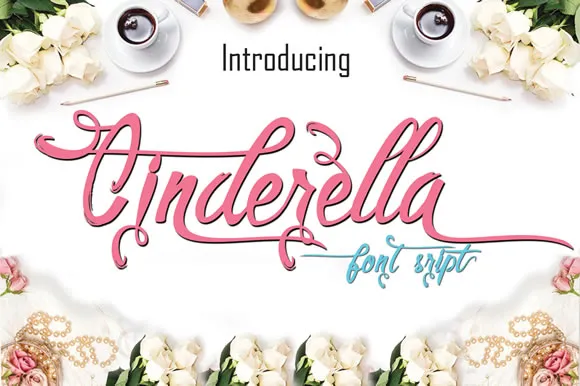
Cinderella Script Font – Download Grátis
Cinderella Script é uma fonte script moderna que transmite a elegância do antigamente refinado com a suavidade dos traços delicados. Embora seja uma criação moderna, apresenta detalhes meticulosos e linhas arredondadas criadas pelo traçado de um canivete pontiagudo e elegante. É uma mistura entre o clássico e o contemporâneo, trazendo uma sensação sofisticada à qualquer texto que seja seu porta-voz. Ideal para aplicativos como cartazes de eventos, logotipos de marcas ou mesmo para manusear em sites, Cinderella Script capturará a atenção do público com sua textura refinada e personalidade única.